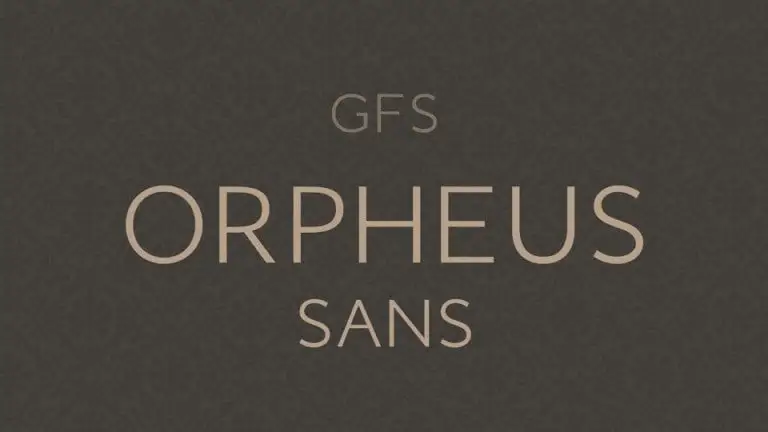
Esta é uma elegante fonte de tipo sans serif desenvolvida pela Greek Font Society. GFS Orpheus Sans Serif é uma versão monolinária do original Orpheus, resultando de um experimento criativo baseado no tipo contrastado que mostra as inovações incorporadas ao longo da desenho inicialmente feito em linhas simples e proporção equilibrada. Este design foi inspirado na ideia moderna de tipo sans serif com linhas monolinerais limpas e proporções equilibradas. Orpheus Sans foi criado pelo designer George Triantafyllakos entre 2015 e 2016. A GFS Orpheus Sans Serif oferece um design único, combinando elegância contemporânea com a simplicidade de uma fonte monolinária, tornando-a ideal para aplicações de design gráfico modernas.